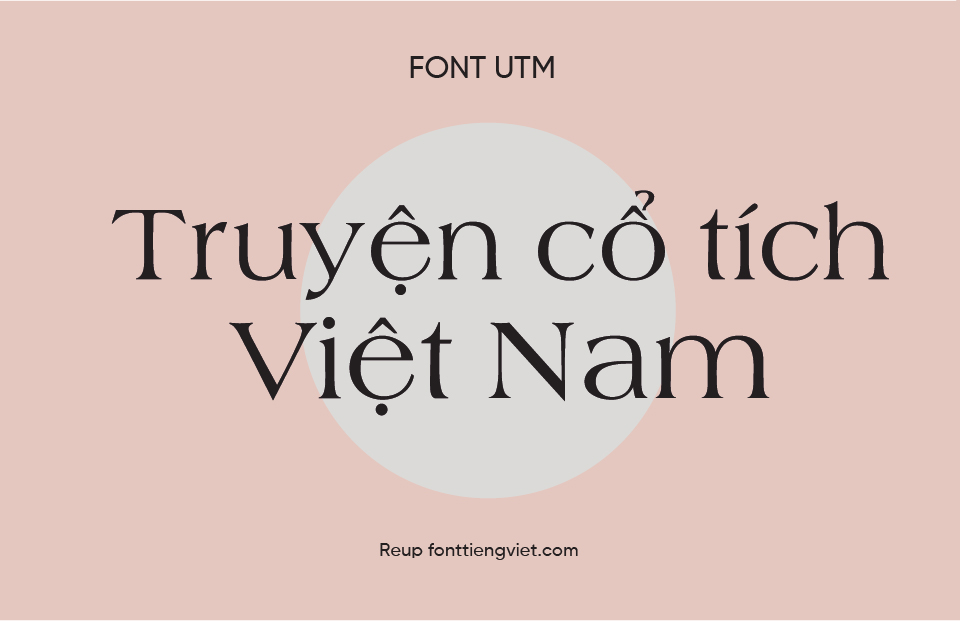
Font việt hóa UTM Amherst
Giới thiệu về Font việt hóa UTM Amherst trong giáo dục
Trong môi trường giáo dục, việc lựa chọn một Font Miễn Phí chất lượng giúp các bài giảng trở nên sinh động và chuyên nghiệp hơn. Font việt hóa UTM Amherst là một trong những lựa chọn hàng đầu nhờ phong cách tối giản nhưng không kém phần hiện đại. Được phát triển dựa trên bộ mã UTM nổi tiếng, bộ chữ này đã được tinh chỉnh kỹ lưỡng về dấu câu để phù hợp hoàn toàn với tiếng Việt, giúp người dùng không gặp lỗi hiển thị khi soạn thảo nội dung dài.
Ưu điểm nổi bật của bộ Font việt hóa UTM Amherst
Thiết kế thanh lịch và dễ đọc
Đặc điểm lớn nhất của Font việt hóa UTM Amherst chính là đường nét dứt khoát và độ tương phản vừa phải. Điều này hỗ trợ tối đa cho học sinh trong việc tiếp nhận thông tin trên các slide trình chiếu hoặc tài liệu in ấn. Kiểu dáng của font mang lại cảm giác tin cậy, rất phù hợp cho các báo cáo khoa học hoặc đồ án môn học cần sự chỉn chu.
Tính ứng dụng linh hoạt trong nhà trường
Không chỉ dùng cho văn bản, bạn có thể áp dụng bộ font này để thiết kế bảng tin, thiệp mời sự kiện trường học hoặc tiêu đề báo tường. Sự đa dạng trong cách thể hiện giúp các bạn học sinh thỏa sức sáng tạo mà vẫn giữ được sự đồng nhất trong bố cục tổng thể. Đây thực sự là công cụ đắc lực cho những ai yêu thích ngành thiết kế đồ họa cơ bản.